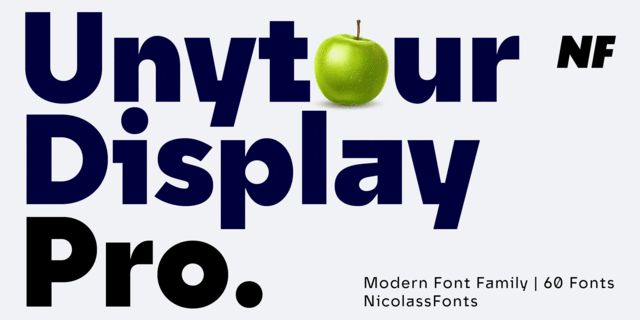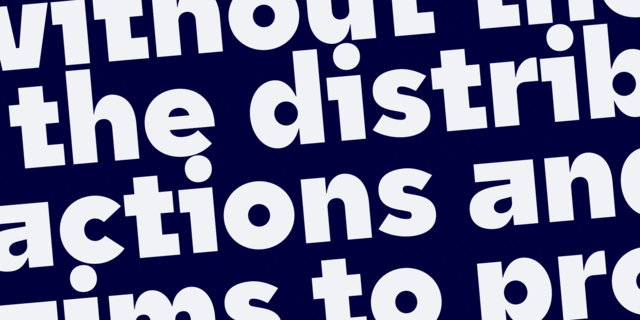
Асоціації зі шрифтом Unytour Display Pro BoldОсобистість і характер шрифта:
важкий, авторитетний, значний, серйозний, переконливий, твердий, залізний, надійний, мужній, впевнений, сталевий, грубий, тоталітарний, стабільний, гучний, рівний, сильний, кондовий, стійкий, політичний, революційний, сміливий, важливий, точний, прямокутний, індустріальний, техногенний, військовий, армійський, монументальний, солдатський, урбаністичний, робочий, мотивуючий, суворий, крутий, залізничний, амбітний, міський, брутальний, ігровий, ламаний, оригінальний, квадратний, експериментальний, дзвінкий, кутастий, рубаний, чіткий, дивний, характерний, незвичайний, модний, цікавий, міцний, статичний
війна, армія, зброя, машинобудування, мітинг, політика, шахта, завод, металургія, танк, тренажери, верстат, інструмент, будівництво, будматеріали, тара, склад, порт, ящик, патрони, архітектура, конструктор, креслення, техніка, промисловість, електростанція, енергетика, революція, ремонт, урбаністика, депо, шахтар, шолом, уніформа, вагон, авіація, літак, страйкбол, блокбастер, бойовик, екшен, взуття, цегла, вантажівка, далекобійник, мотор, двигун, залізниця, Місто, робочий, страйк, Протест, кубики, лего, реп, концерт, дизайн, інтер'єр, гра, анімація, електроніка, селфі, головокрутка Шрифт асоціюється з віком: